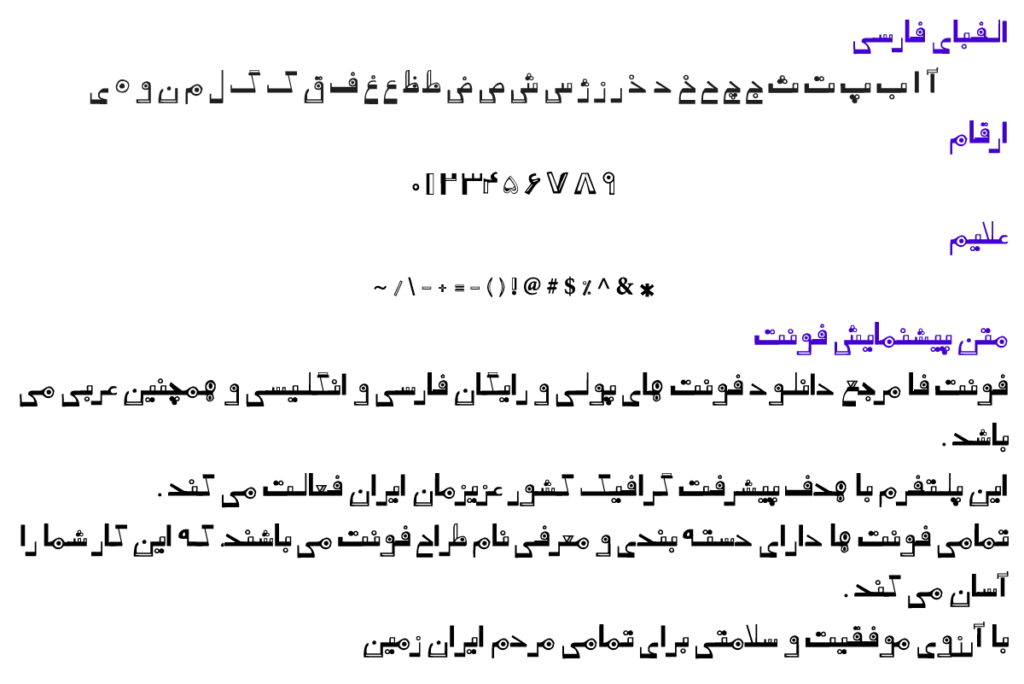
فونت فارسی رفاقت – Refaghat
طراح فونت: فاطمه ملکی نوع فونت: فونت فانتزی
توضیحات و معرفی فونت رفاقت
فونت فارسی رفاقت ( Refaghat ) از مجموعه فونت های آزاد می باشد، همینطور نوع فونت فانتزی می باشد.
فونت زیبای مرتبط توسط فاطمه ملکی طراحی و ساخته شده است.
در تصویر زیر شعر قدیمی وطن با این تایپ فیس زیبا و فانتزی نوشته شده است.